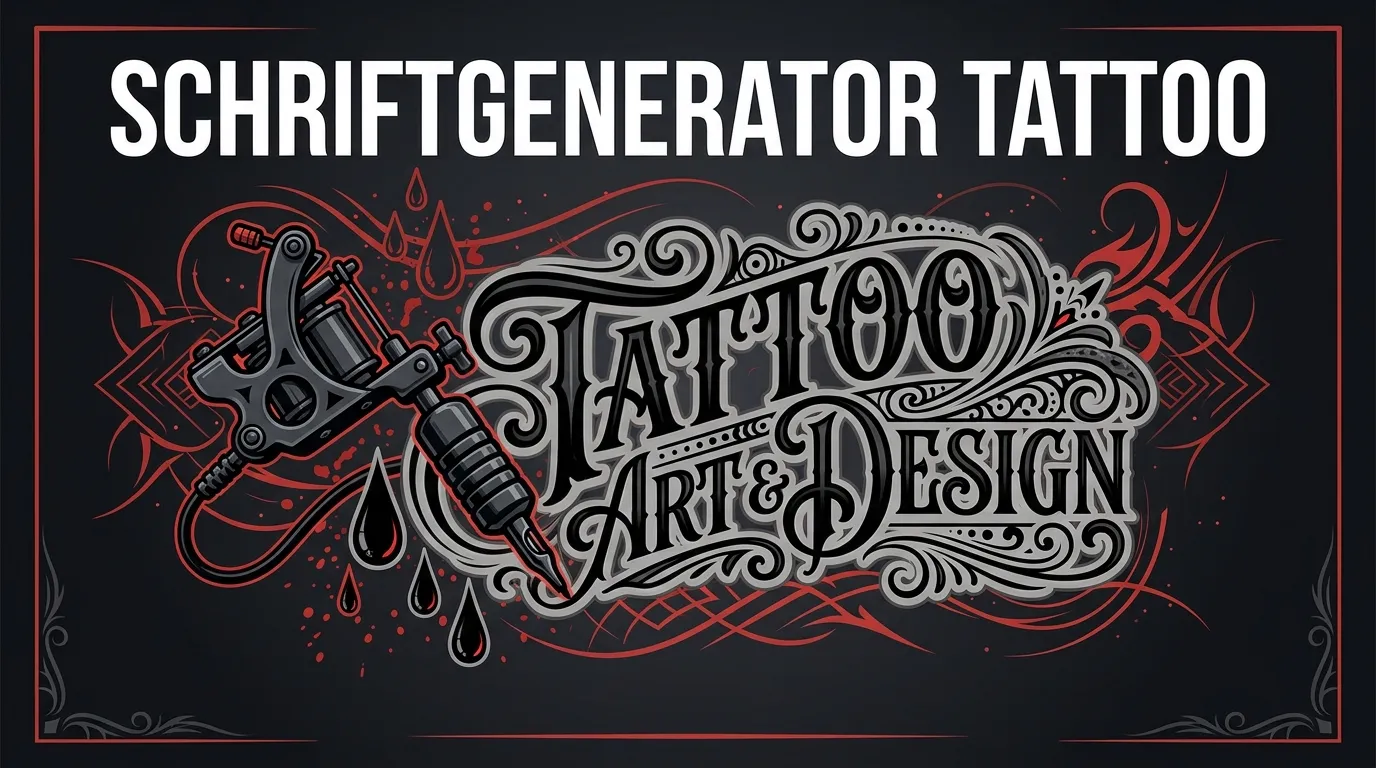
Tattoo Schriftgenerator: Dein Text in echter Tattoo-Schrift
Tipp zur Haltbarkeit
Sehr dünne Linien (Fineline-Stil) und extrem kleine Schriftgrößen (<4 cm) können mit der Zeit auf der Haut an Schärfe verlieren. Für langlebige Tattoos empfehlen wir Schriften mit mittlerer Strichstärke und eine Mindestgröße von 5 cm.
Hinweis: Umlaute (ä, ö, ü, ß)
Deutsche Umlaute und ß haben keine Schriftgenerator Tattoo-Entsprechung im Unicode-Standard und erscheinen daher in normaler Schrift neben den umgewandelten Buchstaben. Das ist eine unvermeidliche technische Einschränkung aller Schriftgenerator Tattoo-Generatoren, nicht ein Fehler unseres Tools.
Tattoo-Schrift live testen: ohne Termin im Studio
Bevor du dich für eine Tattoo-Schrift entscheidest, willst du sehen, wie dein Text wirklich aussieht. Unser Generator zeigt dir den Schriftzug sofort in mehreren Stilen: Gothic, Script, Fineline, Blackletter und Handschrift: und lässt dich Größe und Körperstelle simulieren.
So gehst du besser vorbereitet ins Tattoo-Studio: Du weißt schon, welcher Stil dir gefällt, wie groß der Text sein soll und ob die Umlaute korrekt dargestellt werden. Das spart Zeit und reduziert Enttäuschungen.
Welche Tattoo-Schrift passt zu welcher Körperstelle?
Die Wahl der Schrift hängt stark von der Körperstelle ab: Für das Handgelenk eignen sich feine Script- und Fineline-Schriften (5-8 cm Länge). Am Unterarm wirken Gothic und Blackletter besonders eindrucksvoll (8-15 cm). Für Rippen und Rücken sind längere Zitate in eleganter Schreibschrift beliebt.
Als Faustregel gilt: Je kleiner und filigraner die Schrift, desto glatter und flacher sollte die Hautstelle sein. Auf stark gebogenen oder beweglichen Stellen (Finger, Handfläche) verlieren sehr dünne Linien schneller an Schärfe.
1. Umlaute (ä, ö, ü, ß): Im Bild-Export werden alle deutschen Sonderzeichen korrekt dargestellt. Im Unicode-Modus hängt es vom Stil ab: wir kennzeichnen Einschränkungen transparent.
3. Haltbarkeit: Filigrane Schriften (Fineline, Script) verblassen tendenziell schneller als kräftige Blockschriften (Gothic, Blackletter). Wir empfehlen für Langzeit-Lesbarkeit eine Mindestgröße von 5 cm und mittlere Strichstärke.